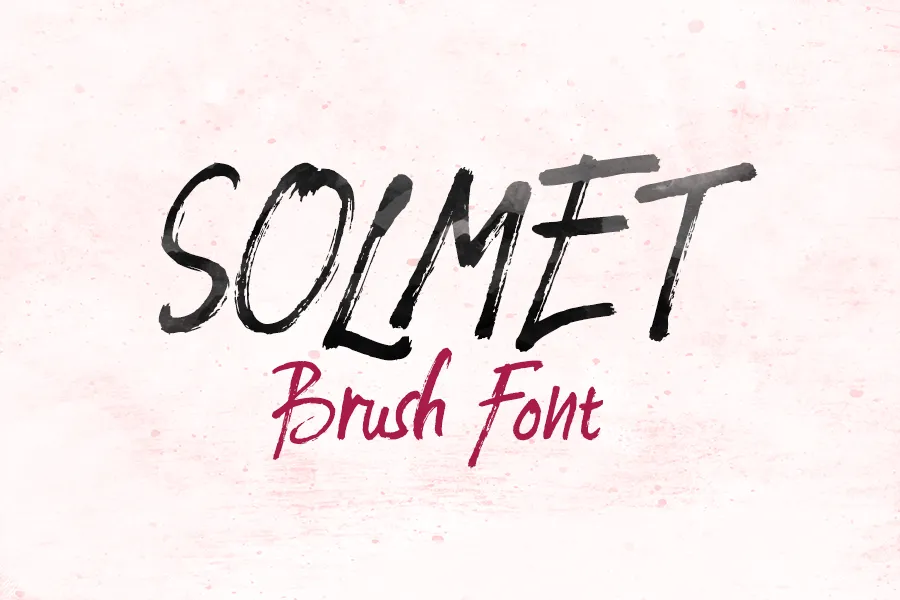
Solmet Marker Font – Download Grátis
A Solment é uma fonte do tipo à mão-dura de marcador natural que combina escrita alegre de pessoa com detalhes ressaltados de um marcador duro. Esta fonte é perfeitamente imperfeita, tornando-a um recurso ideal para destacar seu mensagem e chamá-la atenção entre as muitas opções disponíveis. Na categoria de fontes à mão-dura, o Solment é uma escolha que oferece tanto beleza natural quanto uma personalidade vibrante, criada para quem busca um estilo autêntico em seus projetos digitais. Inspirada pelo ritmo das escritas a mão e pelos detalhes únicos dos marcadores, esta fonte se destaca por sua capacidade de tornar mensagens singelas ainda mais vivas e memoráveis. Não perca essa oportunidade única para enriquecer suas criações com um toque autêntico e único.